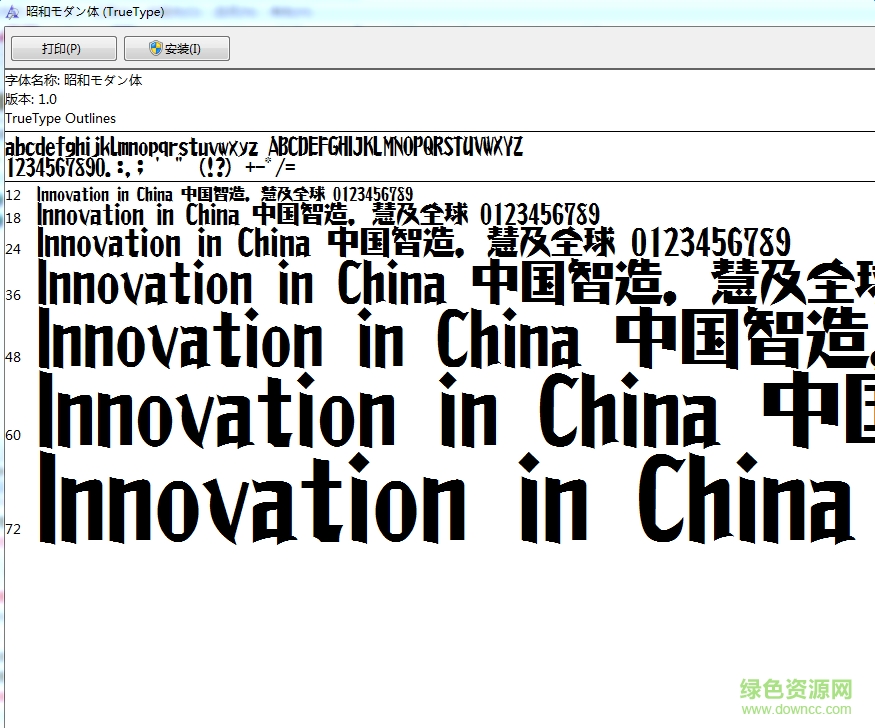
日本昭和體字體是一款古典粗黑風格字體軟件,昭和體筆畫工整,撇捺尾部細膩,非常獨特有創(chuàng)意,整體效果比較醒目耐看,感興趣的朋友歡迎來綠色資源網(wǎng)下載體驗!
日本昭和體字體是一款應用于藝術設計方面的簡體中文字體,該字體筆畫粗壯,尾部的甩尾有力且有豐富的筆觸細節(jié),大字效果突出且引人注目;并且最大程度還原作者書寫字形,細節(jié)表現(xiàn)完整,且字庫完整,可以廣泛應用于名片設計、新聞媒體、宣傳海報、ppt、影視制作以及內容用字等領域。
該字體筆畫細膩,每個字體所占空間一致,給人非常清爽簡單的感覺,非常的好看!